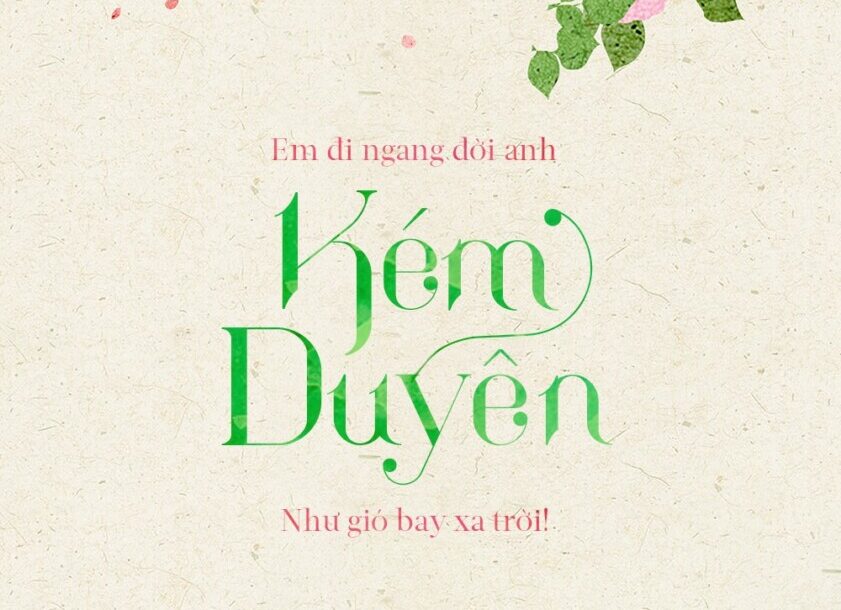
Trong thế giới thiết kế đồ họa, việc lựa chọn một Font Chữ phù hợp có thể tạo nên sự khác biệt lớn cho tác phẩm của bạn. Đối với những dự án đòi hỏi sự sang trọng, tinh tế và một chút hơi hướng high-fashion, không thể bỏ qua Font Việt hóa MTD Fashion Vogue. Đây không chỉ là một phông chữ; nó là tuyên ngôn về phong cách và đẳng cấp. Đặc biệt với học sinh, sinh viên đang chuẩn bị cho các dự án cuối khóa hay báo cáo tốt nghiệp, việc sử dụng một font chữ chuyên nghiệp như MTD Fashion Vogue sẽ giúp bài làm của bạn nổi bật hơn rất nhiều. Hãy cùng tìm hiểu sâu hơn về bộ font chữ cao cấp này, tại sao nó lại được yêu thích đến vậy, và làm thế nào để tận dụng tối đa vẻ đẹp của nó trong các ấn phẩm sáng tạo của bạn.
Sức Hút Khó Cưỡng Của Font Việt hóa MTD Fashion Vogue Trong Thiết Kế
Font Việt hóa MTD Fashion Vogue là đại diện tiêu biểu cho phong cách typography hiện đại, lấy cảm hứng từ những tạp chí thời trang danh tiếng toàn cầu. Sự kết hợp hoàn hảo giữa các nét thanh mảnh, duyên dáng và cấu trúc chữ cái rõ ràng, dứt khoát mang lại cảm giác sang trọng, chuyên nghiệp. Điểm mạnh lớn nhất của phiên bản Việt hóa là khả năng hỗ trợ đầy đủ các dấu tiếng Việt, đảm bảo tính thẩm mỹ không bị phá vỡ khi sử dụng trong nội dung tiếng Việt. Điều này vô cùng quan trọng đối với các nhà thiết kế Việt Nam và các bạn học sinh, sinh viên cần tạo ra tài liệu học tập, poster hay bìa sách hoàn chỉnh. Sự tinh tế trong từng đường nét giúp font chữ này trở thành lựa chọn hàng đầu cho các ấn phẩm in ấn cao cấp, logo thương hiệu, hoặc tiêu đề các bài thuyết trình quan trọng.
Nhiều người lầm tưởng rằng các font chữ “thời trang” chỉ phù hợp với lĩnh vực may mặc, làm đẹp. Tuy nhiên, MTD Fashion Vogue đã chứng minh điều ngược lại. Tính linh hoạt của nó cho phép nó được sử dụng rộng rãi trong các lĩnh vực giáo dục, công nghệ, hay thậm chí là các ấn phẩm học thuật yêu cầu tính nghệ thuật cao. Khi bạn cần một tiêu đề thu hút, dễ đọc nhưng vẫn thể hiện được sự đầu tư nghiêm túc vào mặt thị giác, font này sẽ là trợ thủ đắc lực. Việc sở hữu một phông chữ chất lượng cao như thế này giúp các dự án cá nhân và học tập của học sinh trung học nổi bật hơn hẳn, đặc biệt khi chuẩn bị cho kỳ thi tốt nghiệp hoặc các dự án đầu vào đại học.
Làm Thế Nào Để Áp Dụng Font MTD Fashion Vogue Hiệu Quả Trong Dự Án Học Đường?
Đối với học sinh trung học và sinh viên đại học, việc sử dụng các công cụ thiết kế chuyên nghiệp đang ngày càng trở nên phổ biến. Font Việt hóa MTD Fashion Vogue có thể nâng tầm các dự án học tập của bạn theo nhiều cách:
- Thiết Kế Bìa Báo Cáo/Tiểu Luận: Sử dụng font này cho tiêu đề chính sẽ ngay lập tức tạo ấn tượng mạnh mẽ, thể hiện sự chuyên nghiệp và gu thẩm mỹ cao của người thực hiện. Độ sắc nét và sự thanh lịch của font làm tăng giá trị thẩm mỹ tổng thể của bài làm.
- Tạo Poster Thuyết Trình: Trong các bài thuyết trình môn xã hội, nghệ thuật, hay kể cả khoa học, một poster có typography đẹp sẽ thu hút người xem hơn rất nhiều. Hãy sử dụng MTD Fashion Vogue cho các đề mục lớn để tạo điểm nhấn, thu hút sự chú ý của giáo viên và ban giám khảo.
- Sáng Tạo Nội Dung Truyền Thông: Nếu bạn đang tham gia các hoạt động truyền thông của trường hoặc câu lạc bộ, font này là lựa chọn tuyệt vời cho các bài đăng trên mạng xã hội, infographic, hoặc thiệp mời sự kiện, mang lại cảm giác độc đáo và “thương hiệu” hơn.
- Ấn Phẩm Kỷ Yếu Tốt Nghiệp: Đối với các dự án làm kỷ yếu hoặc các ấn phẩm lưu niệm cuối cấp, MTD Fashion Vogue tạo ra một phong cách bìa và tiêu đề chương hoàn hảo, vừa trang trọng vừa hiện đại.
Mẹo chuyên gia: Vì MTD Fashion Vogue mang tính chất trang trí cao, hãy cân bằng nó với một font chữ sans-serif đơn giản (như Roboto hoặc Open Sans) cho phần nội dung chính để đảm bảo tính dễ đọc và sự hài hòa tổng thể. Sự tương phản này sẽ giúp tiêu đề của bạn thực sự nổi bật mà không làm mất đi tính chuyên nghiệp trong tài liệu học thuật.
Quy Trình Việt Hóa và Tính Tương Thích Typography Cao
Quá trình Việt hóa một font chữ là một công việc tỉ mỉ, đòi hỏi người thực hiện phải điều chỉnh hàng trăm ký tự và tổ hợp dấu để chúng hiển thị chính xác và hài hòa. Phiên bản Font Việt hóa MTD Fashion Vogue đã được tối ưu hóa để giải quyết triệt để vấn đề lỗi dấu, lỗi kerning (khoảng cách giữa các ký tự) thường gặp ở các font nước ngoài khi gõ tiếng Việt. Sự chuẩn mực này đảm bảo rằng dù bạn sử dụng font trên môi trường in ấn (như Photoshop, Illustrator) hay môi trường văn bản (như Word, Google Docs), kết quả vẫn giữ được vẻ đẹp nguyên bản và không gây khó khăn khi đọc. Đây là một lợi thế lớn cho học sinh, sinh viên cần in ấn tài liệu phục vụ kỳ thi hoặc bảo vệ đề án.
Typography là nghệ thuật sắp đặt chữ. Với MTD Fashion Vogue, người dùng được khuyến khích thử nghiệm với các biến thể chữ hoa và chữ thường, cũng như khoảng cách dòng. Font chữ này thường có trọng lượng (weight) nhẹ hoặc trung bình, rất phù hợp khi được in với kích thước lớn, nhưng cũng cần lưu ý khi sử dụng ở kích thước nhỏ để tránh làm mất đi độ sắc nét của các nét mảnh. Việc hiểu rõ tính chất này sẽ giúp các bạn học sinh, sinh viên áp dụng font vào các dự án học thuật hoặc dự án cá nhân một cách hiệu quả và chuyên nghiệp nhất, tránh sai sót trong khâu trình bày. Sự tinh tế này thể hiện rõ ràng mức độ đầu tư vào chi tiết, một yếu tố quan trọng trong đánh giá chất lượng sản phẩm đồ họa và thiết kế.
Tóm lại, Font Việt hóa MTD Fashion Vogue không chỉ là một công cụ thiết kế, mà còn là một nguồn cảm hứng sáng tạo vô tận. Từ những dự án thời trang cao cấp đến các bài thuyết trình học đường, sự tinh tế và phong cách của font chữ này luôn giúp tác phẩm của bạn đạt được sự chú ý xứng đáng. Đừng ngần ngại khám phá và tải về bộ font tuyệt vời này để nâng cao chất lượng thiết kế của mình. Việc sở hữu và sử dụng các tài nguyên Font Chữ chất lượng cao như MTD Fashion Vogue là bước đầu tiên để bạn trở thành một nhà sáng tạo nội dung chuyên nghiệp và thành công. Hãy bắt đầu hành trình sáng tạo của bạn ngay hôm nay!